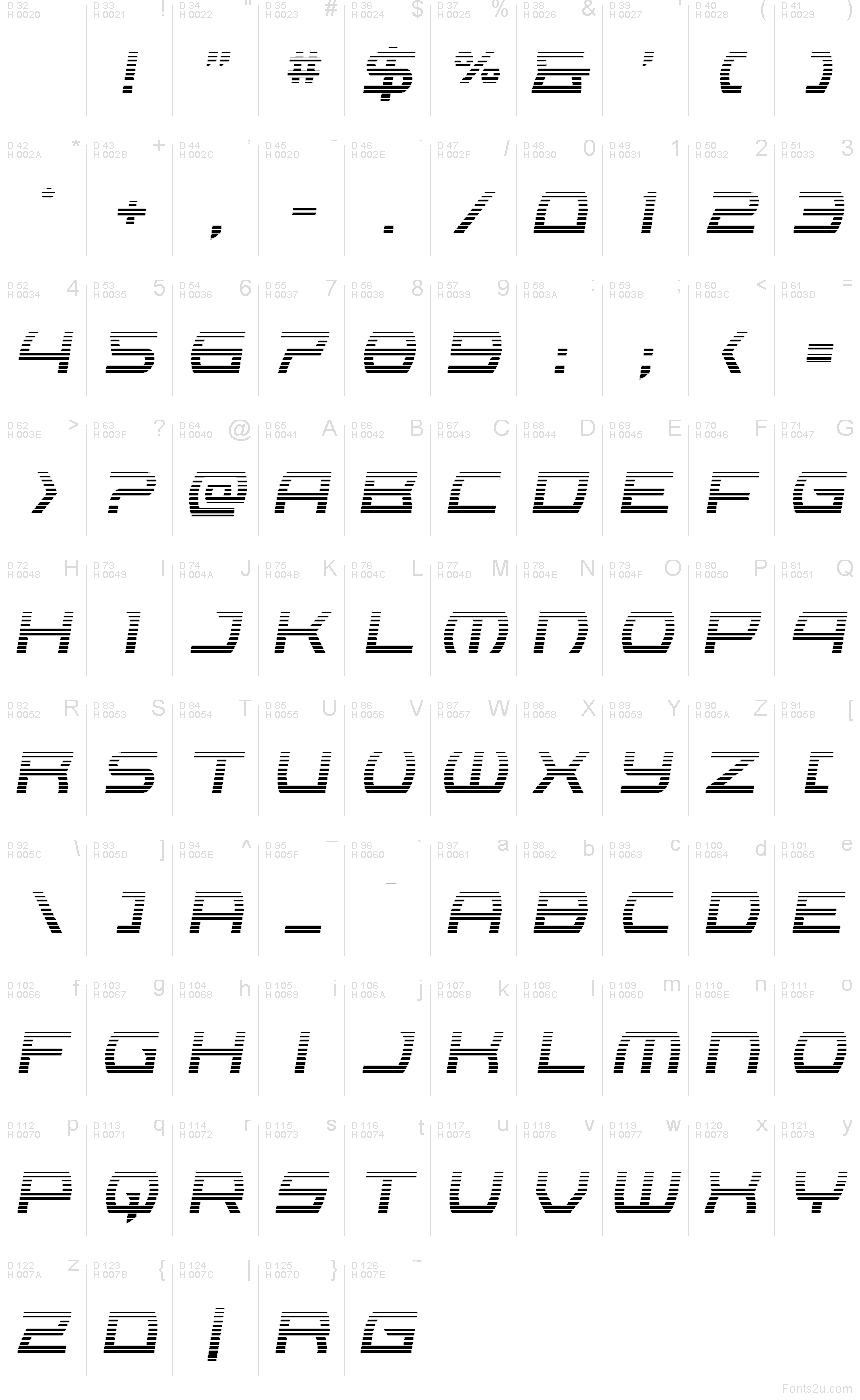
Icemaster Gradient Semi-Italic von Iconian Fonts ist eine kostenlose, futuristische Display-Schrift mit einem schnellen, geneigten Rhythmus und gestreiften Buchstaben, die wie von Geschwindigkeitslinien durchschnitten wirken. Die Großbuchstaben lehnen sich in breiten, geometrischen Formen nach vorne, während die wiederkehrenden horizontalen Unterbrechungen einen kühlen, technischen Look erzeugen, der dem Alphabet einen eleganten Sci-Fi-Puls verleiht.
Die Schrift passt perfekt zu Gaming-Logos, Tech-Postern, E-Sport-Branding, Titelkarten und kurzen Überschriften, bei denen ein kostenloser Font mit eingebauter Dynamik die visuelle Arbeit übernimmt. Setzen Sie sie ein, wenn das Schriftbild selbst Schnelligkeit und Mechanik vermitteln soll – besonders ideal für kurze Texte in Versalien, Monogramme oder Interface-Überschriften.